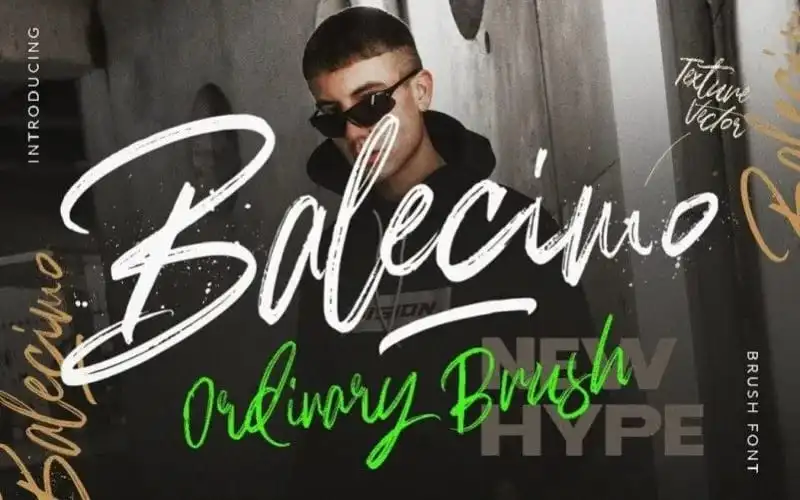
Balecimo Brush Font – Download Grátis
Esta Balecimo Brush Font é perfeitamente adaptada para aplicativos que exigem uma mão-dilatada qualidade. Perfeita para criações de logotipos e design de roupas, a fonte também se destaca como ideal para impressões ou merchandising. A capacidade do designer Dirtyline Studio em criar este estilo de brush font dá vida à forma ilustrativa dos caracteres, permitindo que você transforme conceitos artísticos em obras completas. Seja para assinatura, logotipos, citações escritas a mão, embalagens de produtos, cabeçalhos, postais, merchandising, mídia social ou cartões de aniversário, a Balecimo Brush é uma escolha perfeita. Sempre que você precisar de um brilho único e autêntico, esta fonte é sua melhor opção.